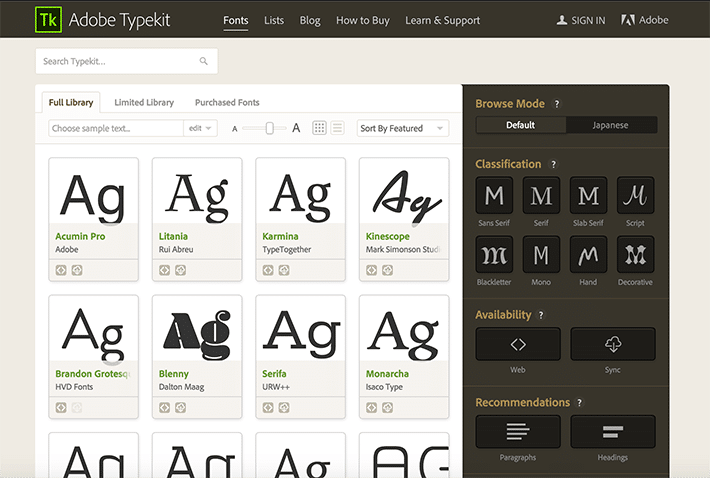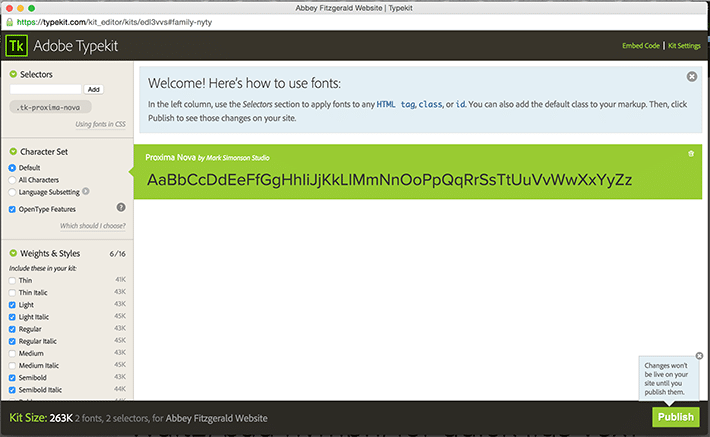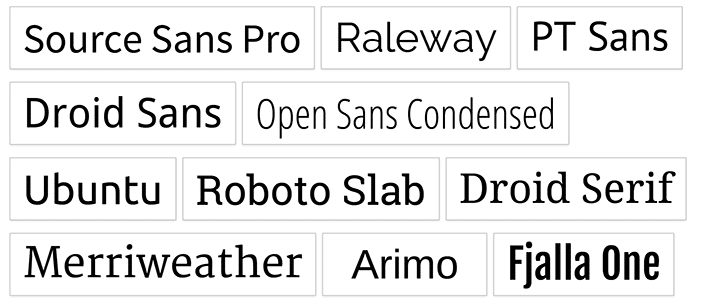
Alles, was Sie über Webfonts wissen müssen
Veröffentlicht: 2022-01-26Typografie ist ein grundlegendes Element in jeder Ihrer Webdesign-Arbeiten. Der Grund, warum wir beauftragt werden, Websites für unsere Kunden zu entwerfen, ist, dass sie ein Erlebnis bieten können, das ihren Benutzern hilfreiche Inhalte bietet. Eine solide typografische Basis hilft dabei, Inhalte so anzuzeigen, dass Benutzer sie effektiv nutzen können. Während es auf einer Website viele andere Designelemente geben kann, ist der Inhalt die Hauptüberlegung, und als Designer ist es unsere Aufgabe, Projekte durch unsere Auswahl und Verwendung von Typografie zu verbessern.
Typografische Grundlagen
Schriftart vs. Schriftart
Bevor wir zu weit in die Typografie-Diskussion einsteigen, lassen Sie uns die Begriffe „Schriftart“ und „Schriftbild“ durchgehen. Eine Schriftart bezieht sich auf den Satz typografischer Symbole und Zeichen: Buchstaben, Zahlen und alle Zeichen, mit denen wir Wörter auf unserer Website platzieren können. Es ist das Design des Alphabets, im Grunde die Form der Buchstaben, die diesen Stil ausmachen. Wenn wir uns auf Helvetica beziehen, beziehen wir uns auf eine Schriftart.
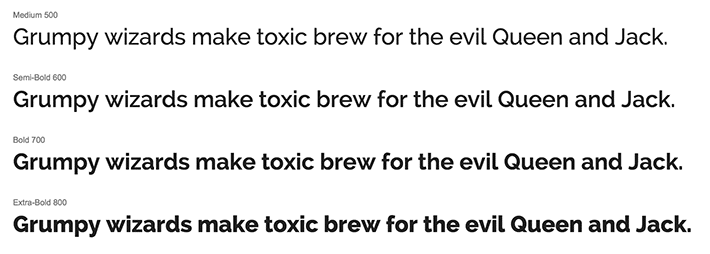
Eine Schriftart ist definiert als der vollständige Zeichensatz innerhalb der Schriftart, der sich häufig auf eine bestimmte Größe und einen bestimmten Stil bezieht. Helvetica Bold 10 Point ist eine Möglichkeit, auf eine Schriftart zu verweisen. Schriftarten sind spezifisch für die Dateien, die alle Zeichen und Glyphen innerhalb der Schriftart enthalten.
Diese großartige Debatte „Schriftart vs. Schriftbild“ sorgt für wunderbare Gespräche mit anderen Designern. Für alle Schreibfreaks da draußen, wir sprechen eigentlich über Schriftarten, aber „Webfonts“ werden am häufigsten in Gesprächen verwendet.
Schriftklassifizierung
Wenn Sie auf die vielen verfügbaren Schriftarten auf der Welt stoßen, müssen Sie mit deren Klassifizierung vertraut sein. Am gebräuchlichsten ist es, sie nach technischem Stil zu klassifizieren: Serif, Sans-Serif, Schrift, Anzeige usw. Schriften werden auch nach anderen Merkmalen wie proportional oder monospaced klassifiziert. Je nach Quelle können sie sehr spezifisch werden.
Geschichte der websicheren Typografie
In den frühen Tagen des Internets waren wir mit websicheren Optionen konfrontiert, die sehr einschränkend waren. Damit ein Benutzer die vom Designer vorgesehene Schriftart sehen konnte, musste diese auf seinem Computer verfügbar sein. Wenn Sie ein Stylesheet von einer älteren Website öffnen, werden Sie wahrscheinlich Arial, Georgia, Times New Roman, Trebuchet MS und/oder Verdana finden. Dies waren die Schriftarten, die am wahrscheinlichsten auf dem Computer eines Benutzers vorhanden waren, sodass sie als „websicher“ galten, da die Mehrheit der Benutzer die Website wie beabsichtigt anzeigen konnte.
Wenn Sie schon seit einiger Zeit Websites entwerfen oder ein langjähriger Websurfer sind, erinnern Sie sich wahrscheinlich an die Tage der begrenzten typografischen Möglichkeiten. Vor nicht allzu langer Zeit sahen wir beim Surfen im Internet immer wieder die gleichen fünf Schriften. Die Dinge sahen ohne andere websichere Optionen langweilig aus, und man könnte argumentieren, dass diese Schriftarten nicht die beste Wahl für das Web waren (schließlich stammen sie aus dem Druck). Aber als sich das Web weiterentwickelte, wurden mehr Typoptionen verfügbar.
Was sind Webfonts?
Da Typografie so wichtig ist, ist es an der Zeit zu feiern, dass große Fortschritte gemacht wurden. Wir haben so viele Schriftarten zur Verfügung, dass wir jetzt auswählen können, was für unsere Benutzer am besten ist, anstatt uns auf dieselben alten websicheren Schriftarten verlassen zu müssen, auf die wir früher beschränkt waren.
Webfonts sind nicht wie websichere Schriftarten auf dem System des Benutzers vorinstalliert. Wir müssen uns nicht darauf verlassen, dass der Benutzer die gewünschte Schriftart auf seinem Computer hat. Sie stammen aus einer mitgelieferten Quelle, sodass jeder Benutzer die definierte Schriftart sehen kann. Diese Schriftarten werden beim Rendern der Webseite vom Browser heruntergeladen und dann auf den Text angewendet.
So verwenden Sie Webfonts
Die @font-face-Regel
Diese weithin unterstützte Regel ermöglicht es uns, Schriftarten von einem Server herunterzuladen oder sie zu hosten, damit wir sie auf unseren Webseiten verwenden können. Indem wir die @font-face Regel in unserem Stylesheet deklarieren, können wir den Namen der Schriftart, den Ort und die Schriftstärke angeben.
Dieses Beispiel zeigt, wie wir Open Sans Regular hinzufügen. Sie werden sehen, dass die Quelle ein Schriftartenordner ist, der im Website-Projekt enthalten ist.
Die obige Deklaration fügt die Schriftart hinzu, damit sie verwendet werden kann. Wie bekommen wir es eigentlich zur Anzeige?
Sie können sehen, dass der Name der Schriftart auf „Open Sans Regular“ eingestellt ist. Dies ist der Schriftartname, auf den dann in unserem CSS-Schriftartenstapel verwiesen wird, zusammen mit Fallback-Schriftarten, falls die Schriftart aus irgendeinem Grund nicht geladen wird. In den meisten Fällen wird die Schriftart problemlos geladen, aber es ist eine gute Idee, für alle Fälle Fallbacks einzuschließen.
Webfonts sind eine großartige Möglichkeit, Ihrem nächsten Webprojekt die perfekte Schriftart hinzuzufügen. Mit einer großen Auswahl an Schriftartoptionen und vielen großartigen Quellen sind Sie nicht mehr an die traditionellen websicheren Optionen gebunden. Webfonts sind einfach zu verwenden und machen Spaß beim Experimentieren. Sie sind eine großartige Möglichkeit, Ihren Website-Projekten Persönlichkeit zu verleihen.